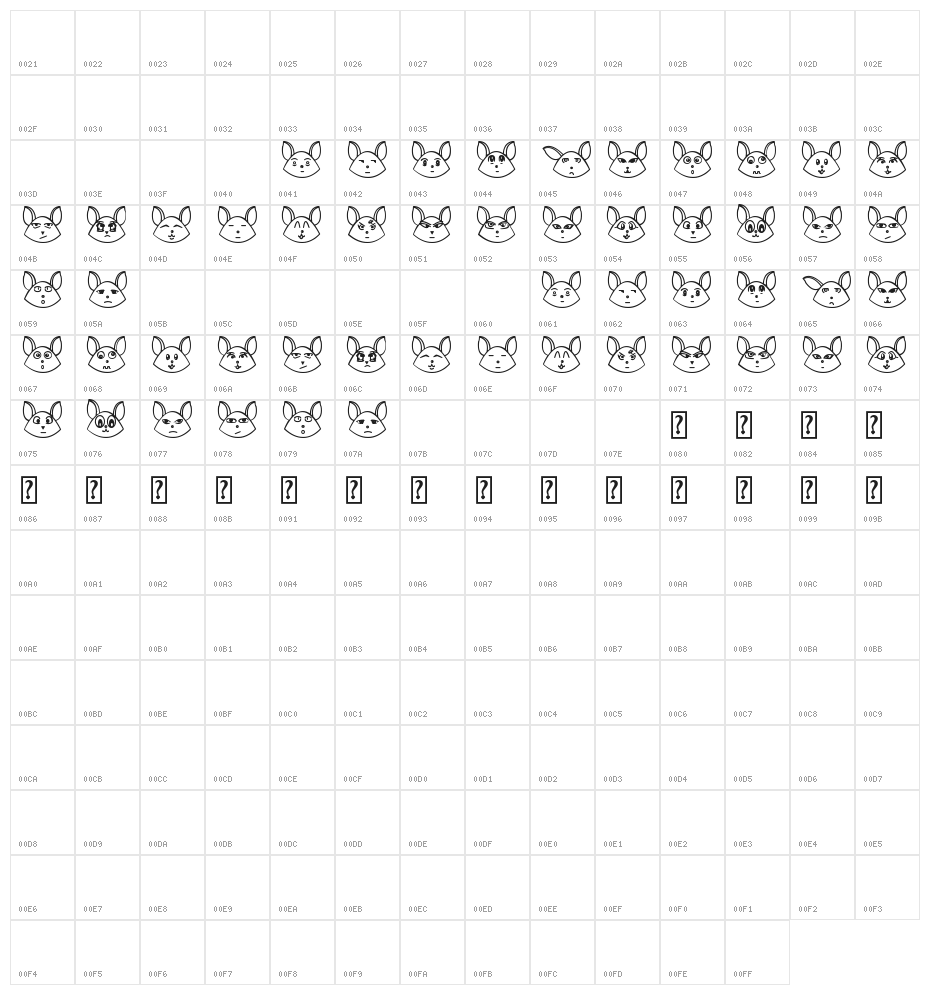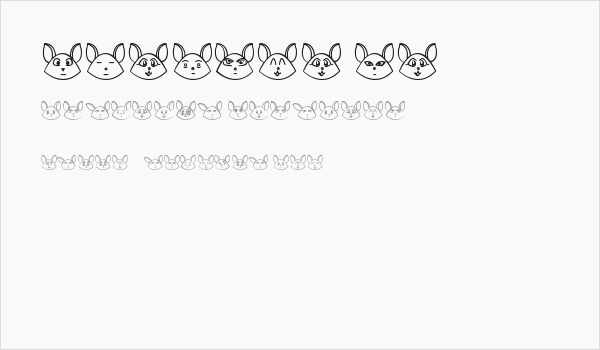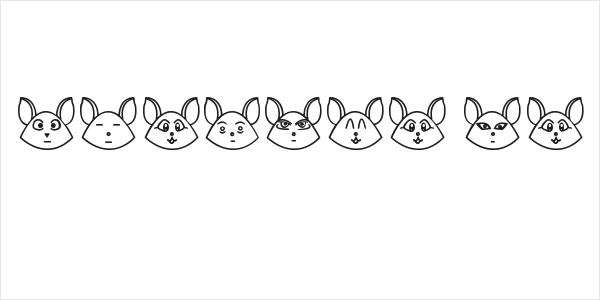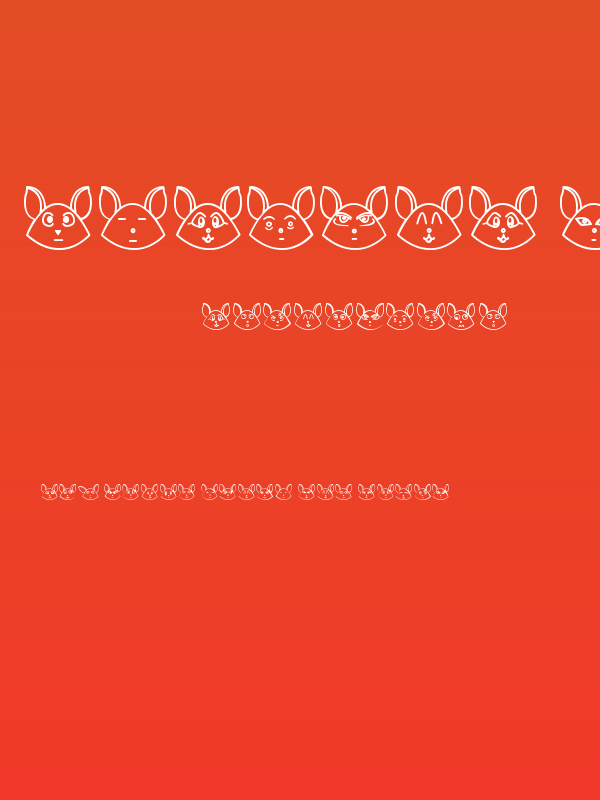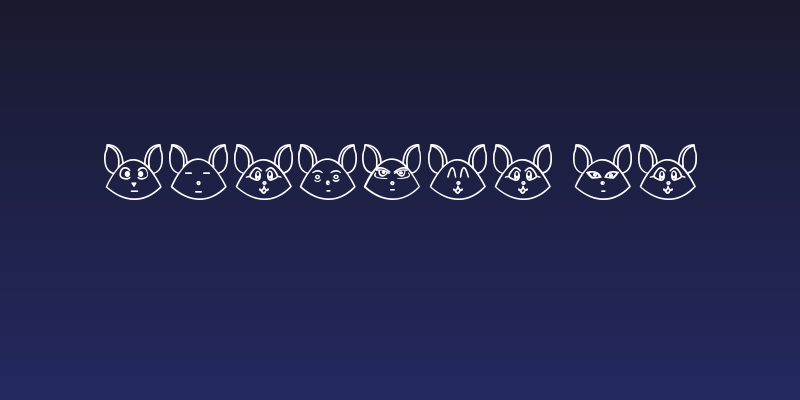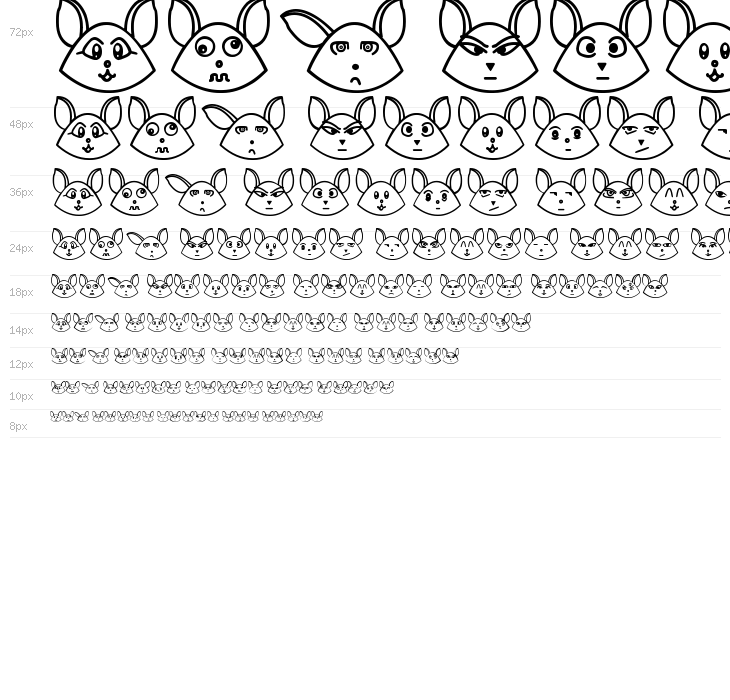
UnTaRot ST Font
✎ Dingbats
| 整体风格 | Playful, Decorative, Whimsical |
| 使用场景 | Logos, Headlines, Posters, Children's materials |
| 推荐项目 | Children's books, educational materials, playful branding, party invitations, greeting cards, and themed posters. |